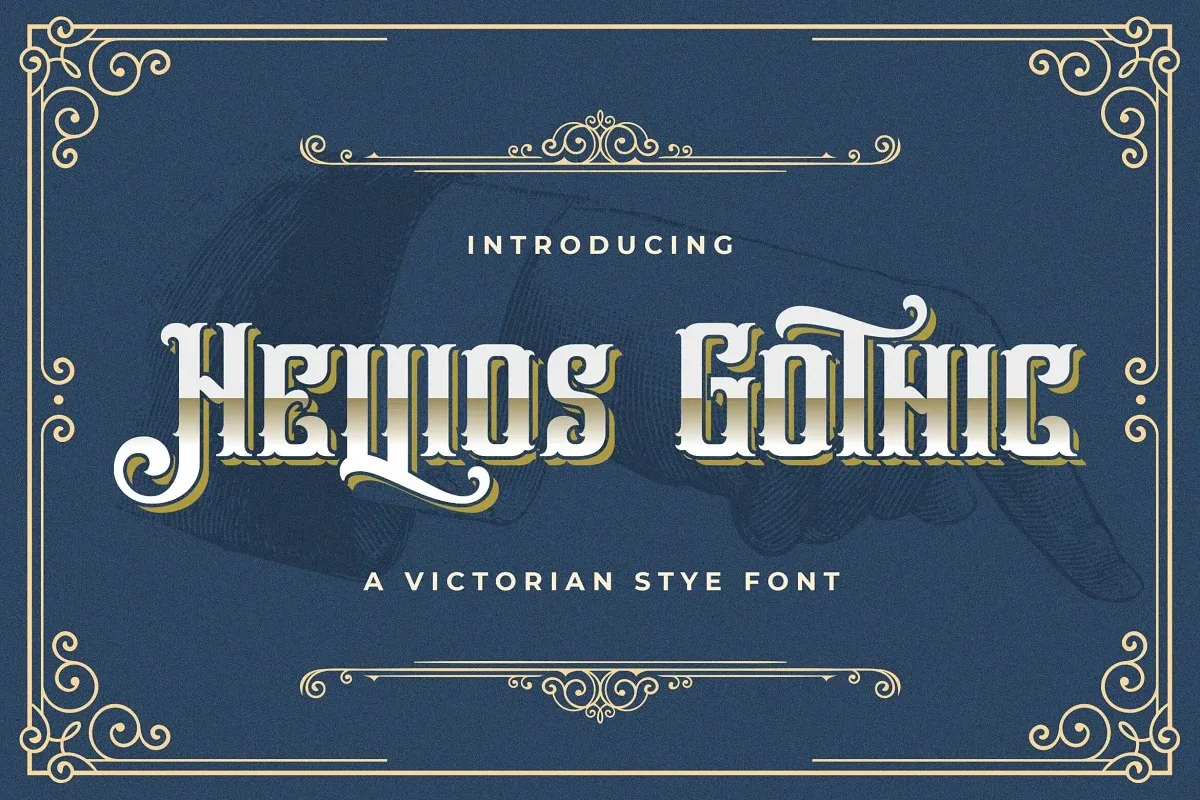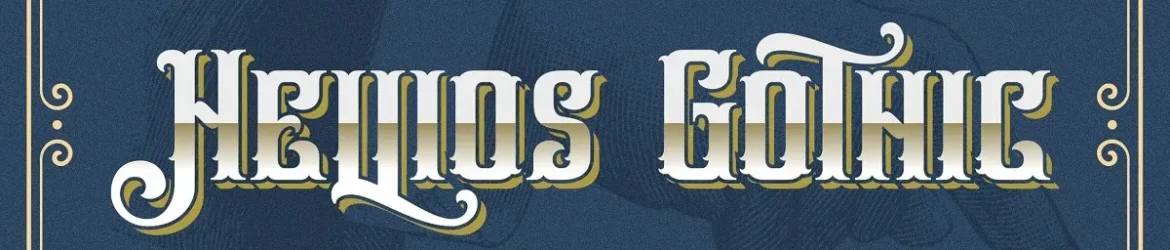
A fonte Hellios Gothic é perfeita para aplicativos onde a elegância e o glamour contagiante são fundamentais — seja para criar uma identidade visual imponente, destacar headlines de um modo sofisticado ou simplesmente adicionar um toque único à sua marca. Trabalhada especialmente para ambientes de apresentação, logotipos e estilos de fontes que exigem destaque, Hellios Gothic oferece tanto letras maiúsculas quanto minúsculas do alfabeto latino, números, sinais monetários e pontuação básica. Esta fonte não é recomendada para uso em texto convencional. A sua beleza está na simplicidade de seu design, que transmite um tom poderoso e elegante. Seja você uma empresa ambiciosa ou um designer desejando dar ao seu projeto um toque único e memorável, Hellios Gothic será sua escolha perfeita para criar o impacto visual que você deseja alcançar. Obrigado a 99designs por oferecermos esta fonte de qualidade excepcional.